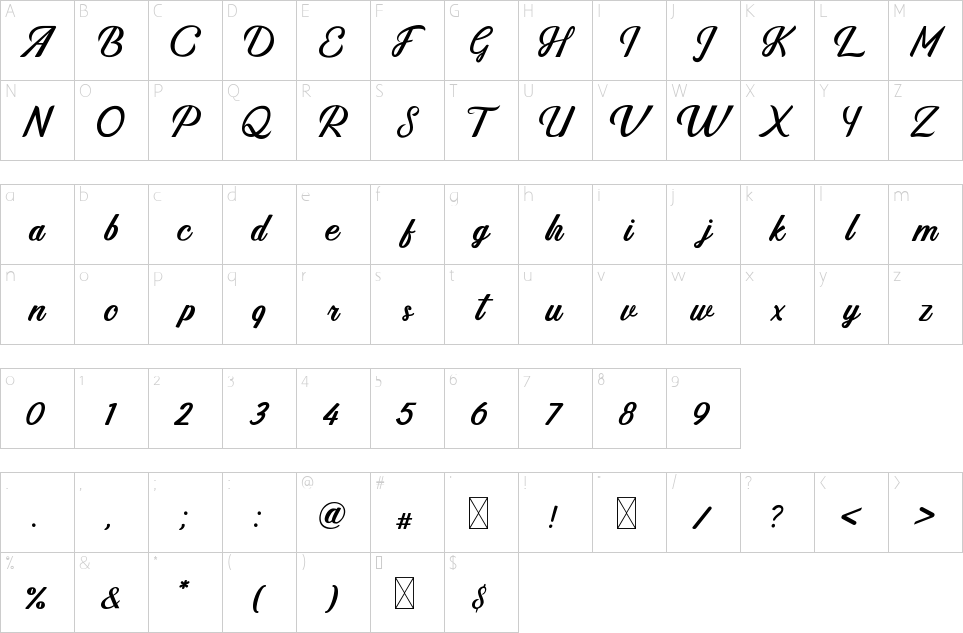
A fonte Jaqueline é um recurso gratuito e incrivelmente elegante para aqueles que desejam adicionar um toque sofisticado a seus projetos digitais. Desenhada pelo uicreativenet, essa fonte se destaca por sua elegância e facilidade de uso, adequada para diversos formatos de design. Com um design cuidadosamente elaborado, a Jaqueline é perfeita para textos de negócios, anúncios, sites, e até mesmo para o design gráfico. Sua simplicidade e eficácia tornam-a uma opção popular para designers iniciantes e profissionais, que buscam uma fonte versátil sem precisar gastar dinheiro extra. Com apenas um clique, você pode adicionar um toque único e profissional a seu próximo design. Seja para um site, uma identidade visual, ou até mesmo para as mensagens de um e-mail, a Jaqueline será uma escolha ótima. Faça o download da Jaqueline Font hoje e experimente a diferença que ela pode fazer em seu trabalho.